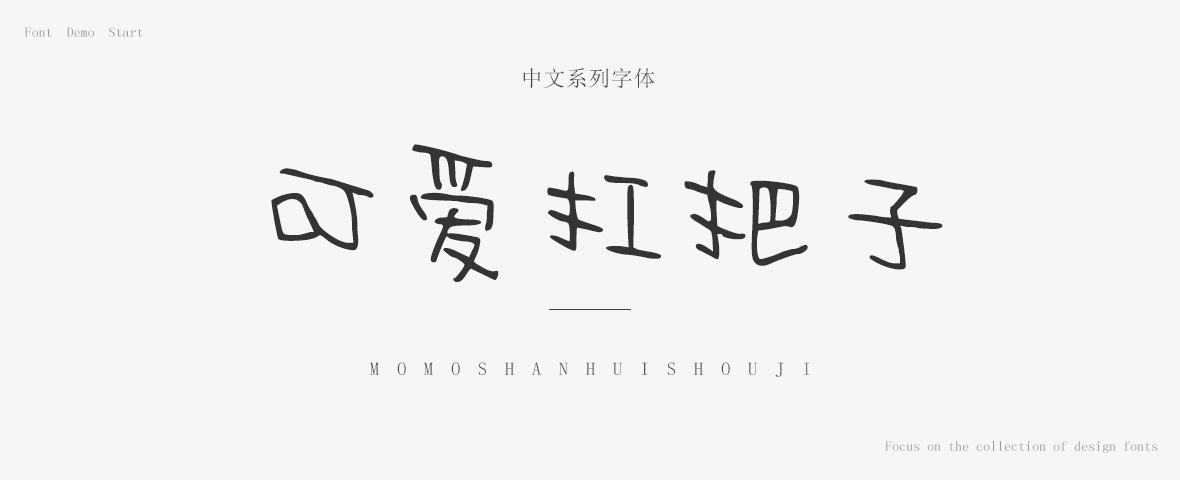
可爱扛把子字体
简介:可爱扛把子字体是一款适合手写艺术字体,字体整体观感酷似天真烂漫的小朋友初学写字——圆润的转角,歪斜的角度,笔画出头较短,自带呆萌可爱气质,字形外轮廓各异,排版时可增加版面的节奏感。适用于童趣、可爱、公益等风格的设计场景,由站长素材整理发布,站长字体下载大全提供精选中英文字体素材。